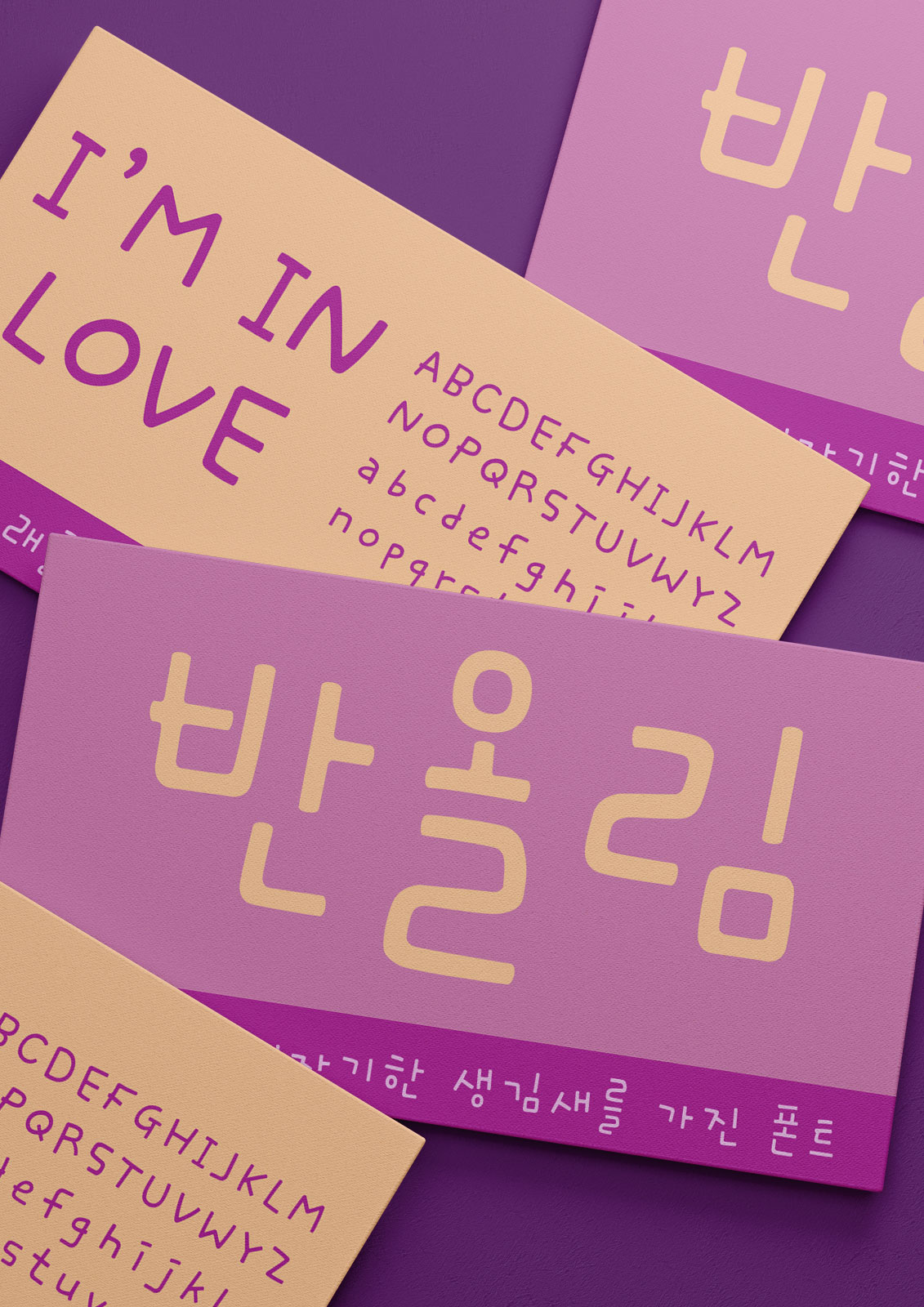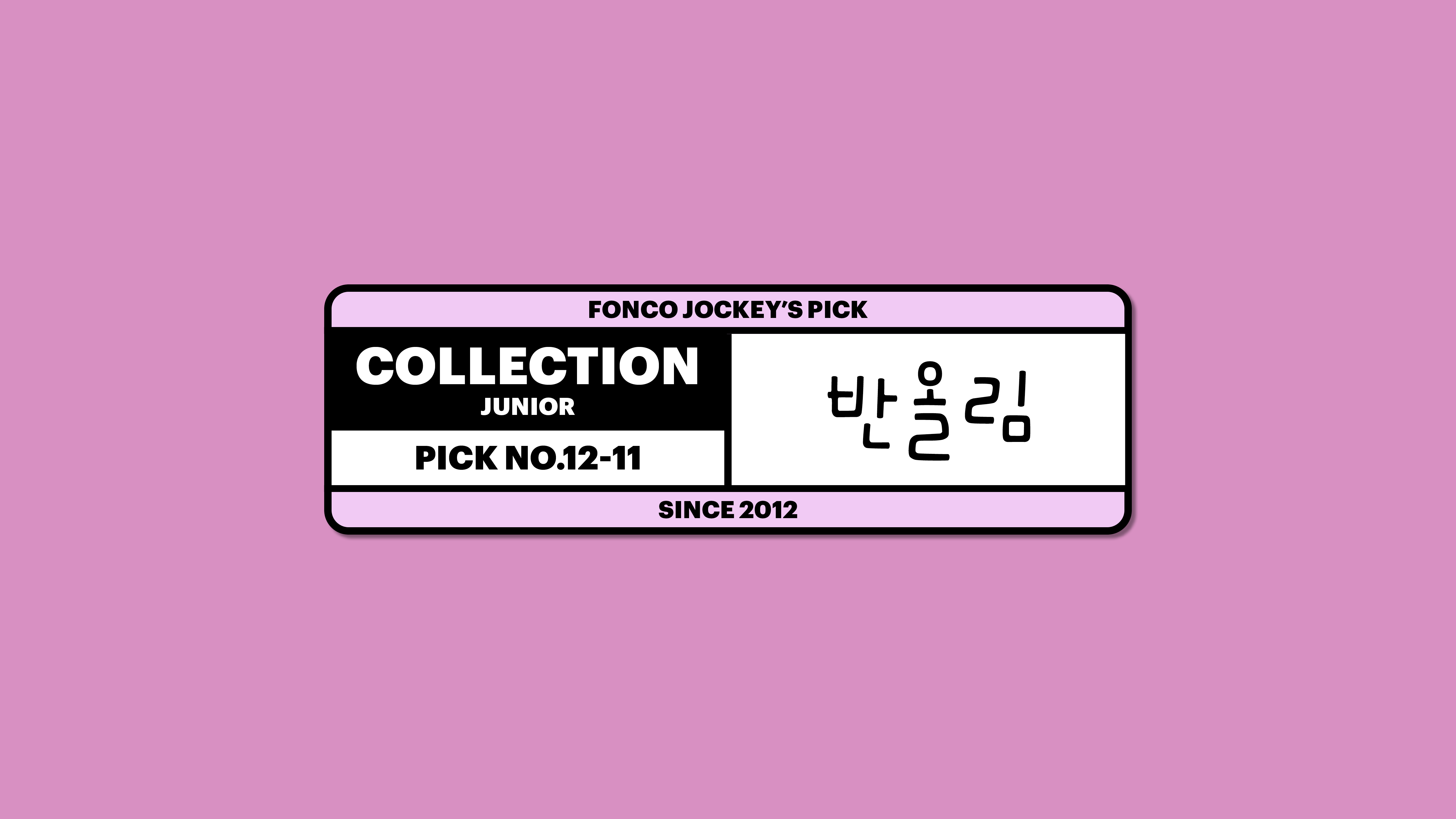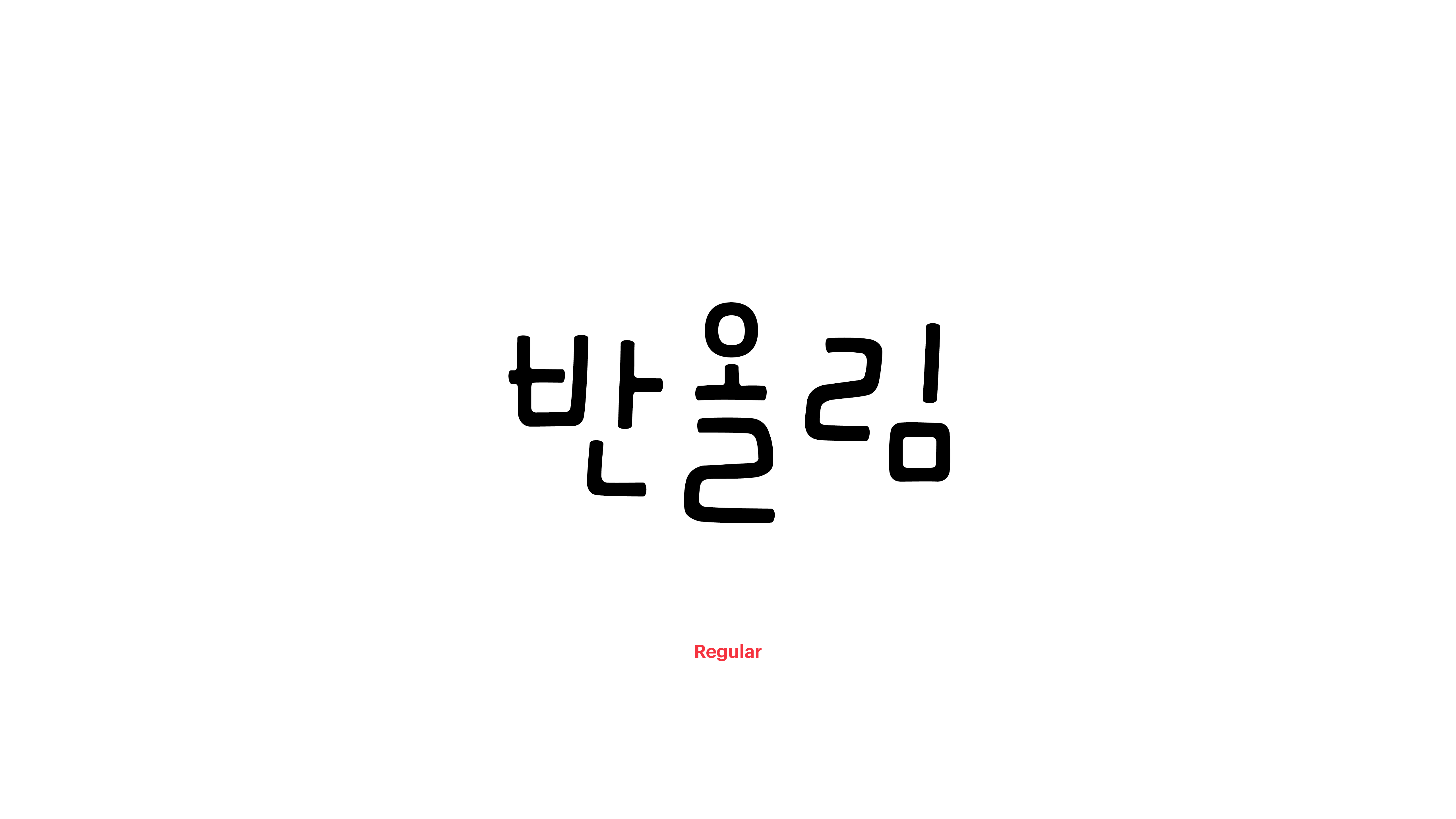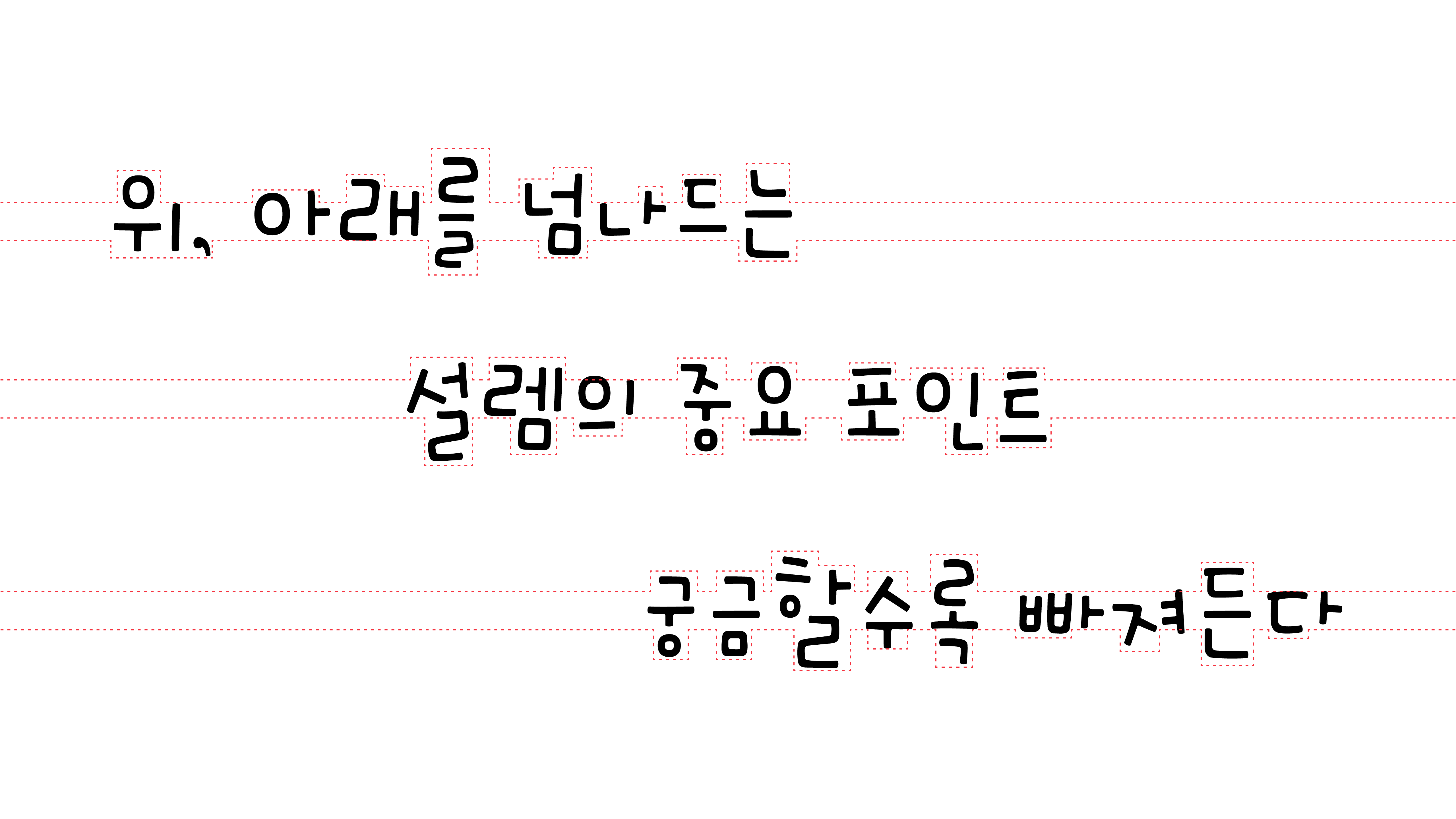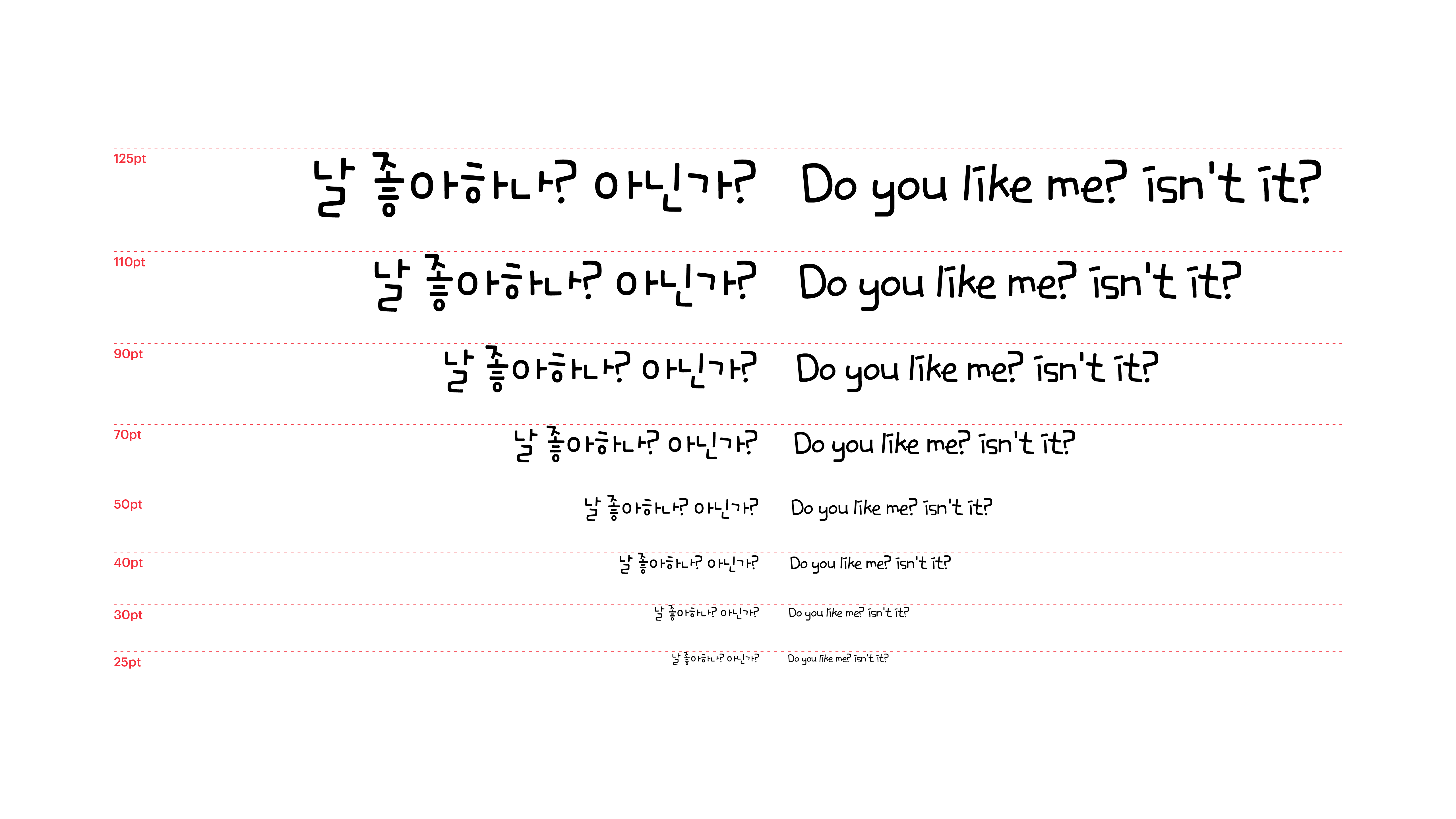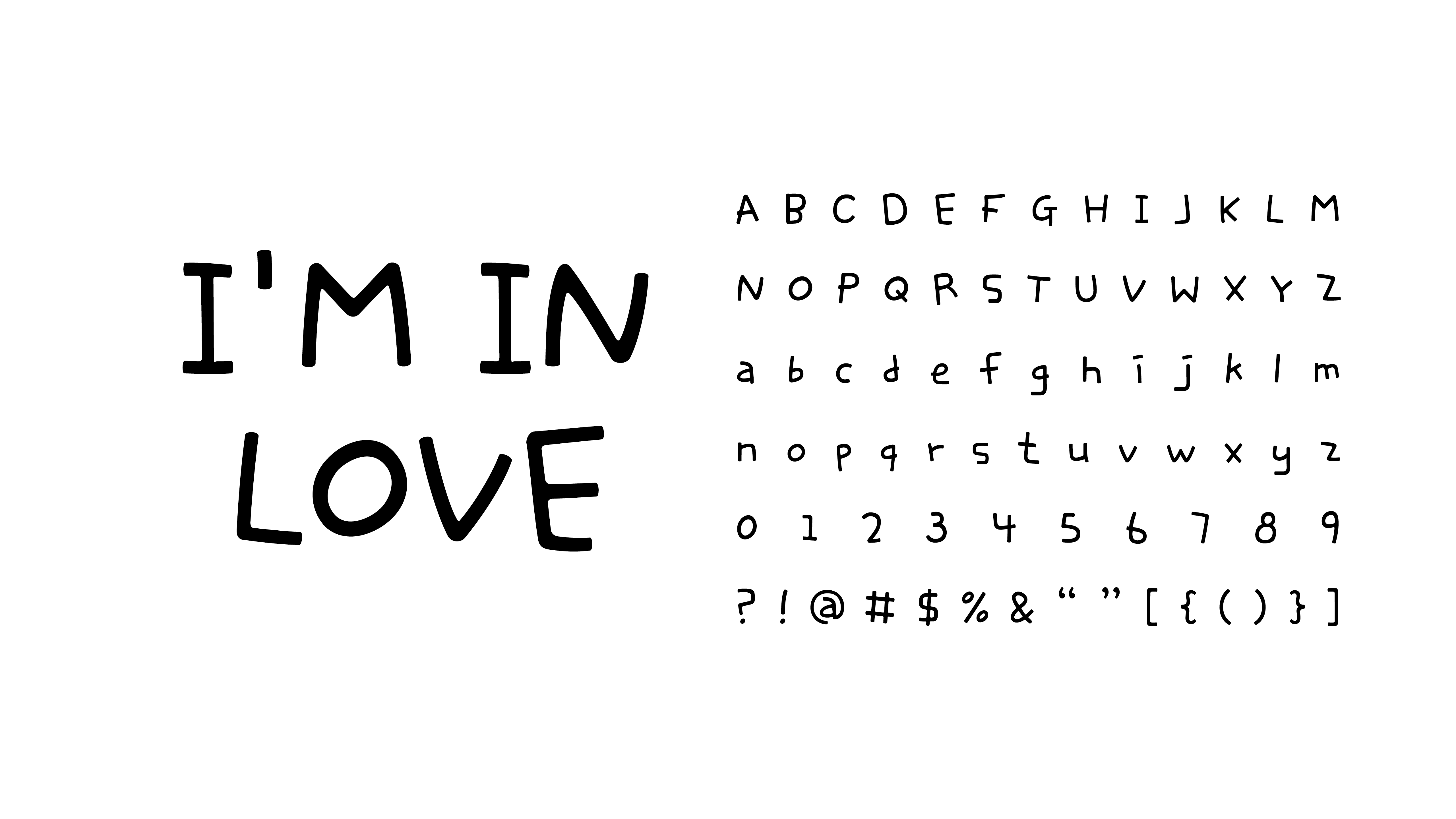
미묘함은 설렘의 중요한 포인트입니다. 날 좋아하나? 아닌가? 궁금해하면 할수록 상대에게 빠져들게 되지요. 동글동글 아기자기한 생김새를 가진 이 폰트는 이래 봬도 썸의 고수입니다. 중간에 위치한 글줄의 위, 아래를 넘나드는 자소들이 우리의 마음을 톡톡 건드리거든요. 넘어올 듯 말듯, 미묘한 기분을 연출하고 싶을 땐 반올림체와 함께하세요.
Yoon 반올림